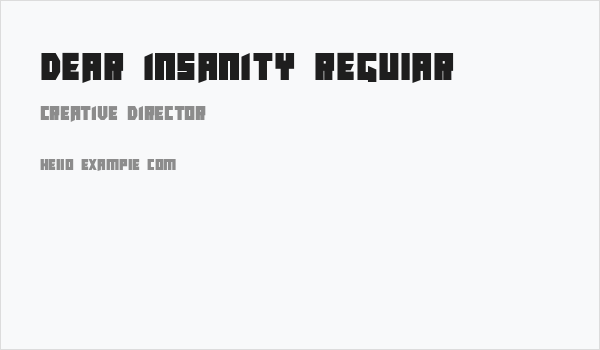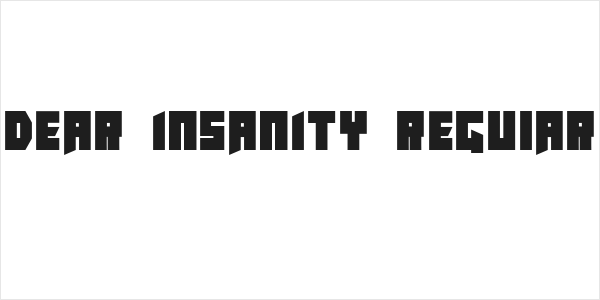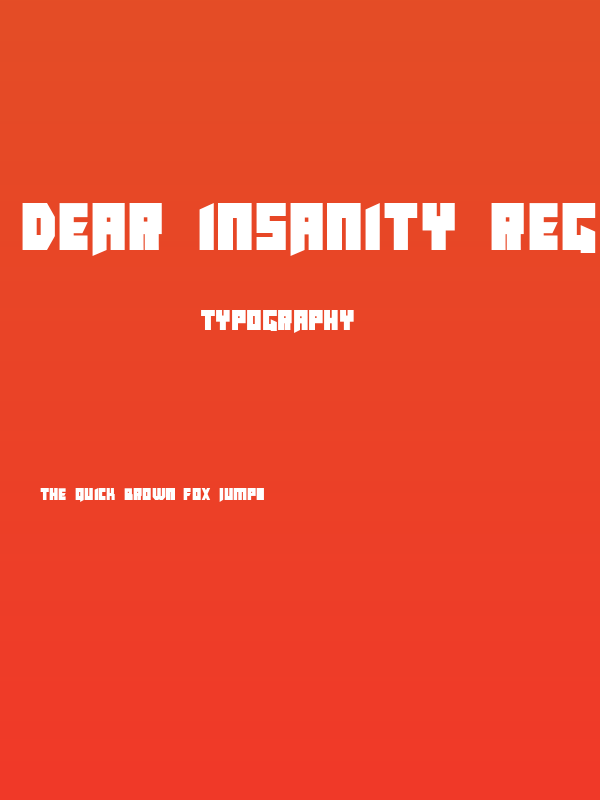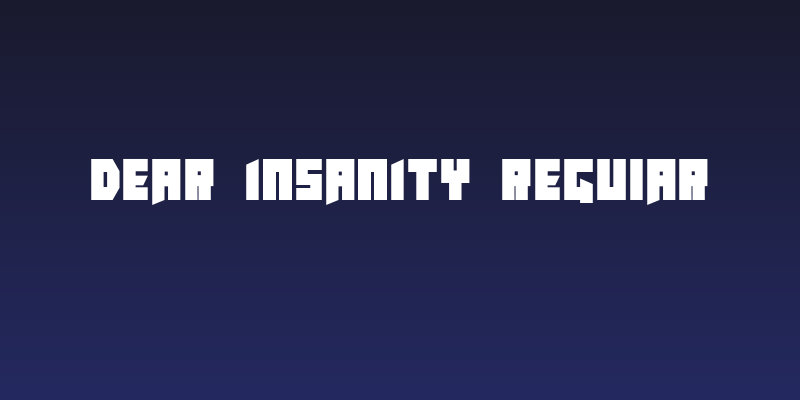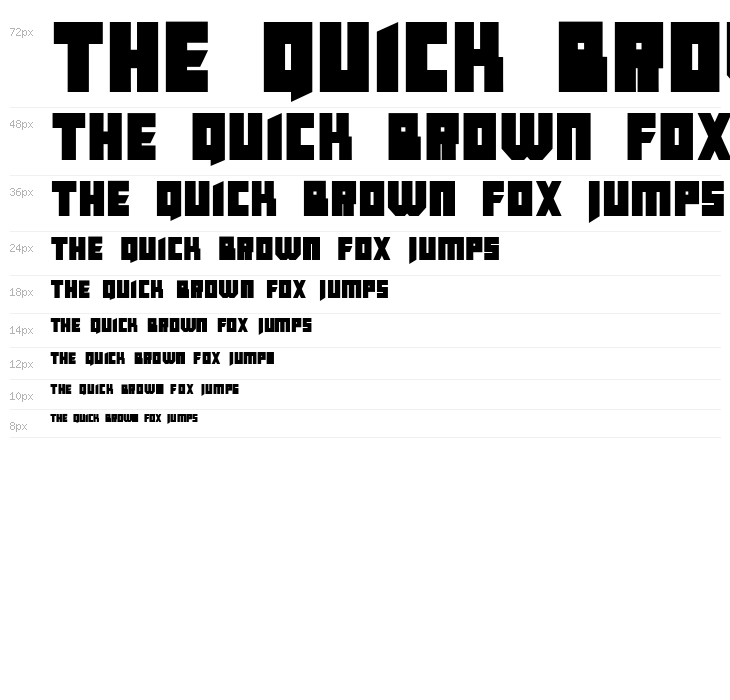
Dear Insanity Regular Font
| Progetti proposti | This font is perfect for projects that require a strong visual impact, such as posters, headlines, logos, and branding materials. Its bold style can also be used in digital media, including video game graphics and website headers. |